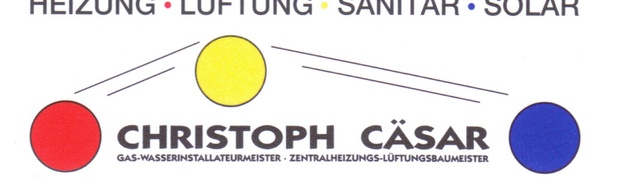
Firmen-Logo-Schriftart gesucht! DRINGEND
ich habe einen Suchauftrag ... für folgendes Logo brauche ich die Schriftart!
Leider weiß mein Chef nochnichtmal wer damals das Logo gemacht hat, ist ca. 10 Jahre her und jetzt soll ich unser Briefkopf abänderen und habe nix :-(.
Es wäre super wenn Ihr mir dort helfen könntet!
Schonmal DANKE für deine Hilfe, habe es ausprobiert ... muss nur sehen wie ich das gezerrt bekomme :-(.
Aber auch diese Hürde werde ich schaffen ....
... muss nur sehen wie ich das gezerrt bekomme :-(.
Aber auch diese Hürde werde ich schaffen ....
Vielleicht kannst Du stattdessen dem Chef gut zureden, daß er auf die Verzerrung verzichtet. Die sieht nämlich ziemlich unprofessionell aus.
Mir gefällt das komplette Logo nicht .... aber das ist schon seit 10 Jahren auf Autos und so weiter ...
Habe sogar festgestellt das die Schriftart schon 2x geändert wurde und jetzt soll es dabei bleiben!
125 % in die Breite und 2 Leerzeichen zwischen Vor- und Nachname
Ich bekenne mich auch der Schriftvergewaltigung schuldig :-)